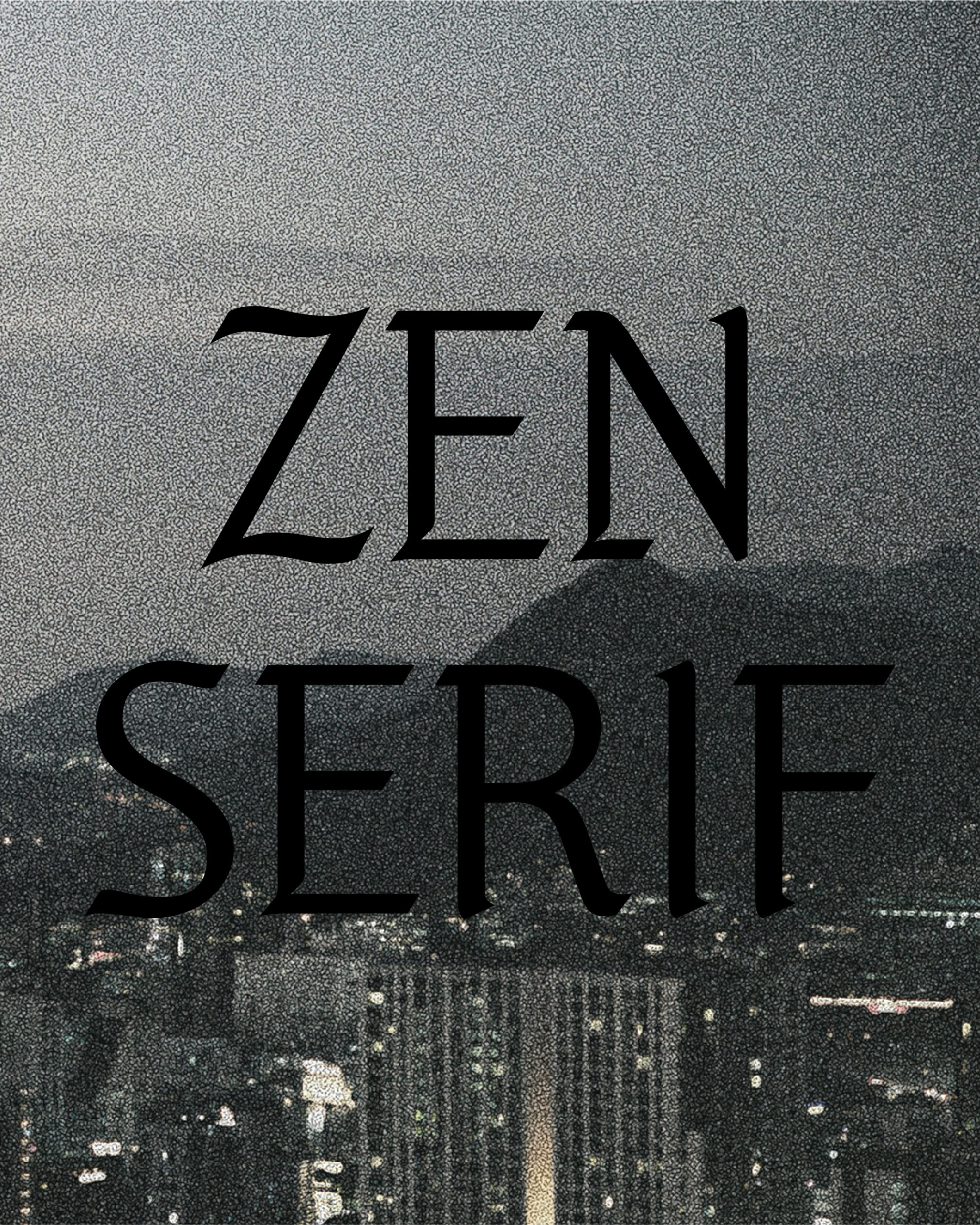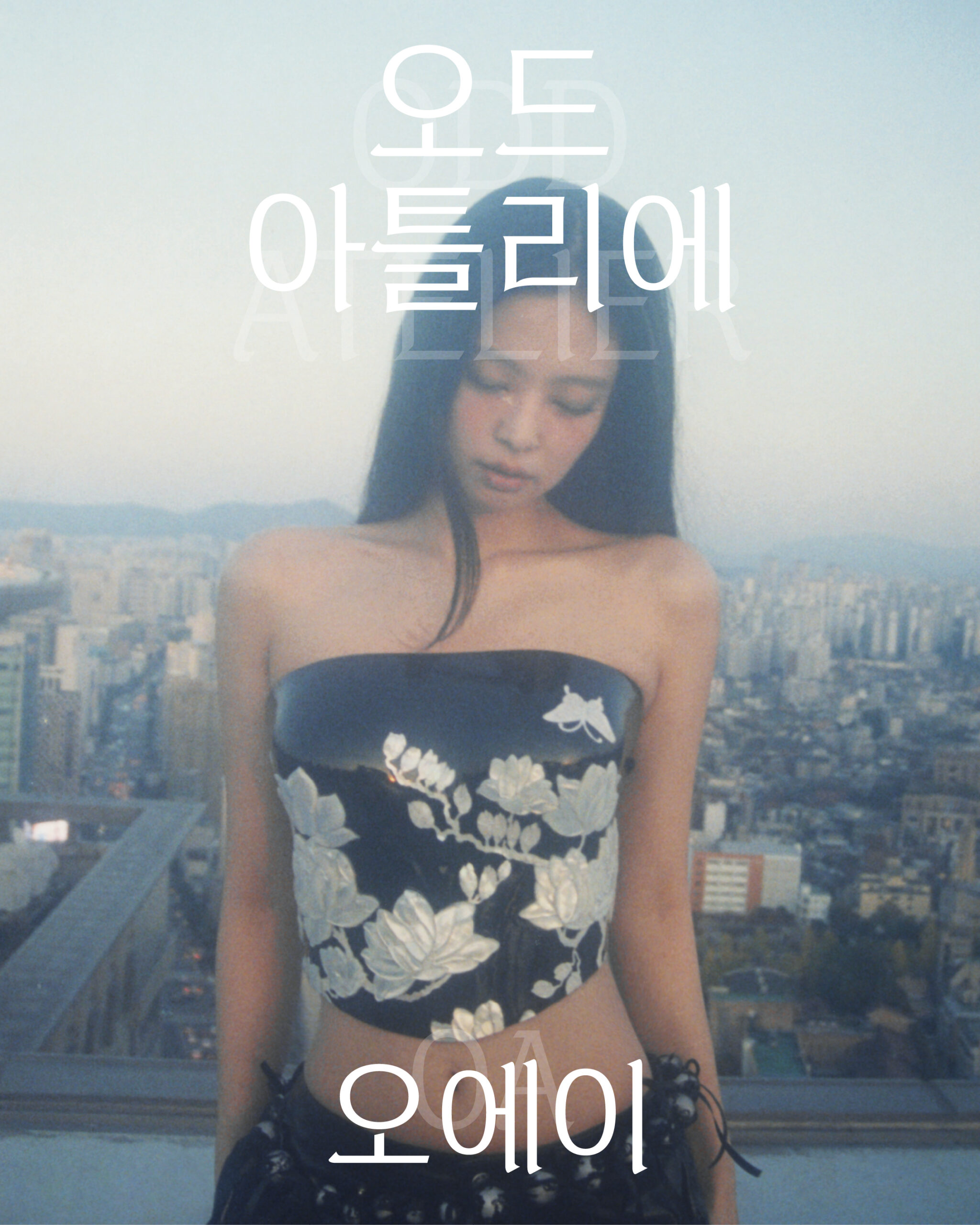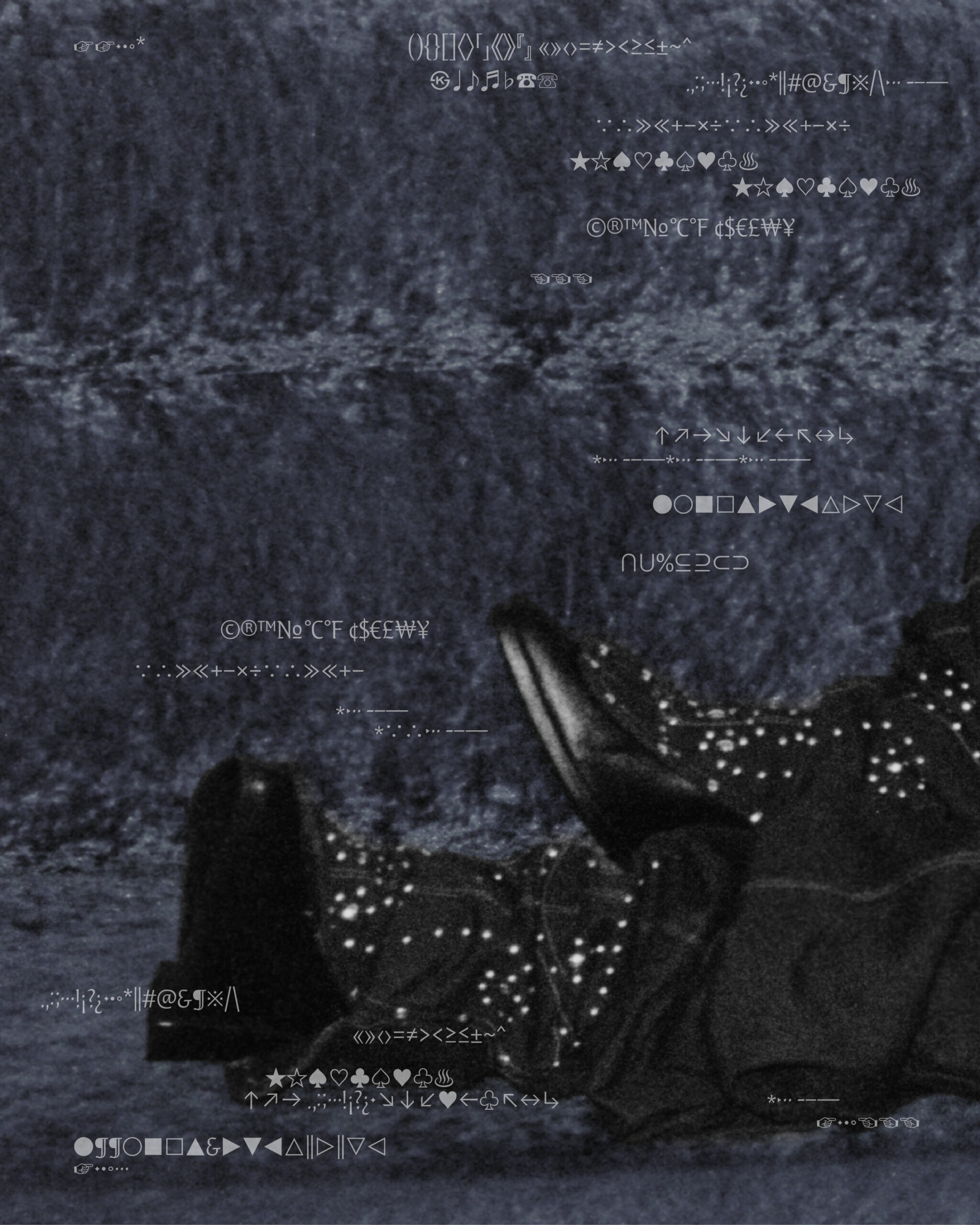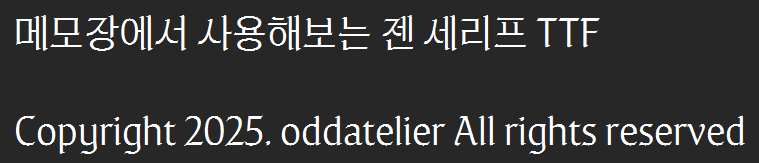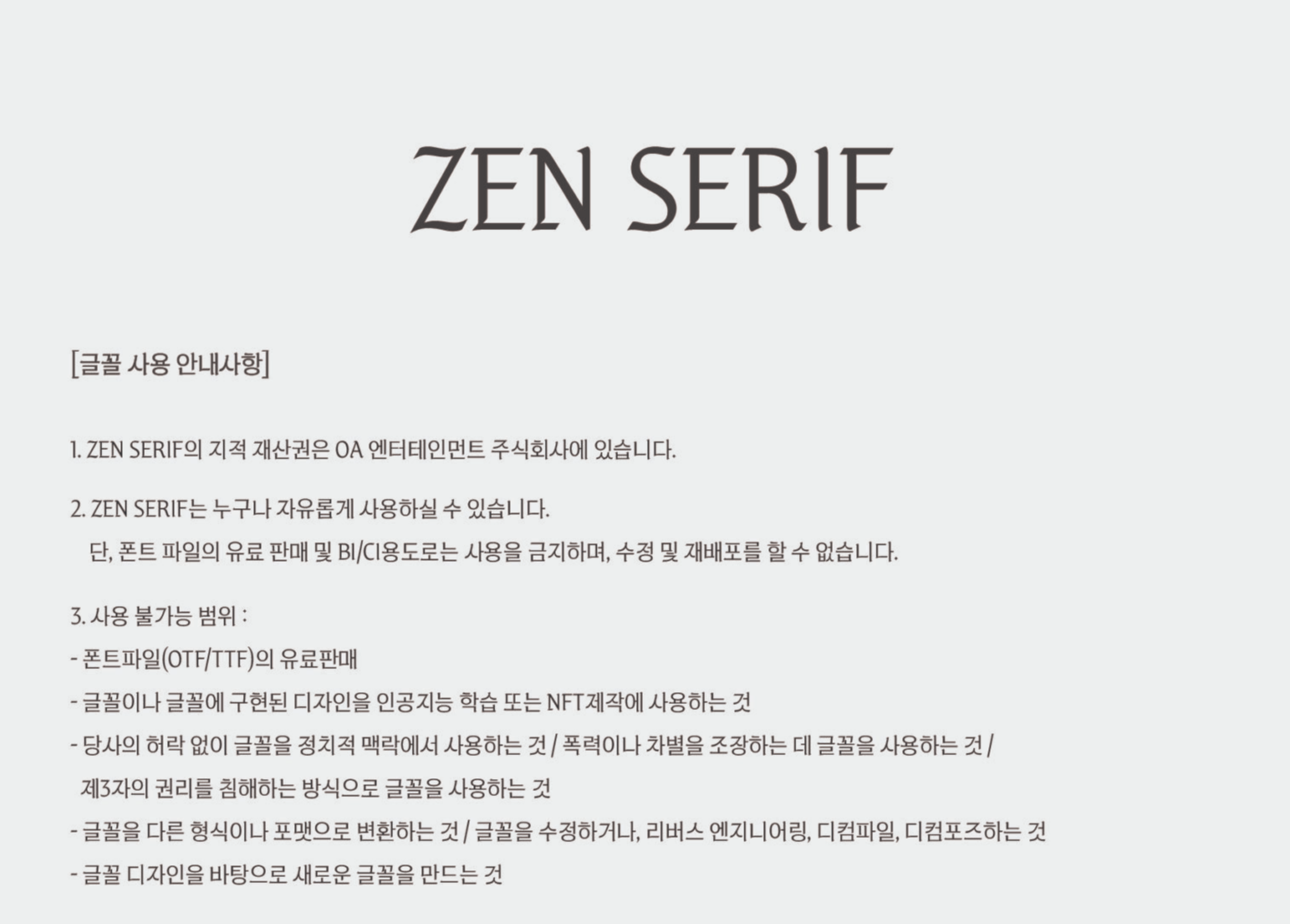
제니, 한글날 맞아 '젠 세리프' 폰트 무료 배포…K-한글 감성 전한 특별한 행보
월드스타 블랙핑크 제니가 한글날(10월 9일)을 맞아 새로운 한글폰트 ‘젠 세리프(Zen Serif)’를 무료로 배포하며 특별한 문화적 행보를 보여주고 있습니다. 이는 단순한 디자인을 넘어, 한글의 미학과 한국 문화에 대한 자부심을 담은 의미 있는 프로젝트입니다.
제니의 정체성을 담은 한글 폰트 ‘젠 세리프’
제니의 소속사 OA엔터테인먼트는 공식 홈페이지를 통해 ‘젠 세리프’ 폰트를 무료 공개했습니다. ‘젠’과 ‘서울 시티’로 K-컬처를 대표해 온 제니는 이번에도 “한국적인 동시에 세계적인 아티스트”로서의 면모를 드러냈습니다.
폰트 디자인은 전통의 미감과 현대적 감각을 조화롭게 결합한 것이 특징입니다. 장식을 최소화해 본질에 집중하면서도, 서양의 블랙레터 서체와의 융합을 통해 누구도 시도하지 않았던 독창적인 시도를 완성했습니다.
한글의 미학을 세계에 알리다
OA 측은 “세종이 누구나 쉽게 글자를 배우도록 한글을 창제했듯, 제니는 그 뜻을 이어 글로벌 팬들에게 한글의 아름다움과 실용성을 알리고자 했다”라고 밝혔습니다. 한글을 사랑하는 마음과 세계적인 영향력을 바탕으로, 제니는 팬들과의 새로운 소통 방식을 제시하고 있습니다.
문화 콘텐츠를 넘는 ‘감다살’ 행보
이번 프로젝트는 제니의 문화적 영향력을 드러낸 ‘감다살(감성, 다채로움, 살림)’ 행보의 연장선으로 볼 수 있습니다. 무대 밖에서도 한국 문화의 가치를 전달하며, 브랜드와 예술의 경계를 허물고 있는 제니의 모습은 팬들뿐만 아니라 업계 관계자들에게도 신선한 영감을 주고 있습니다.
한글날의 의미를 되새기게 한 제니의 이번 행보는, 단순한 기념을 넘어 문화 전파자로서의 책임감과 철학을 보여줬습니다.